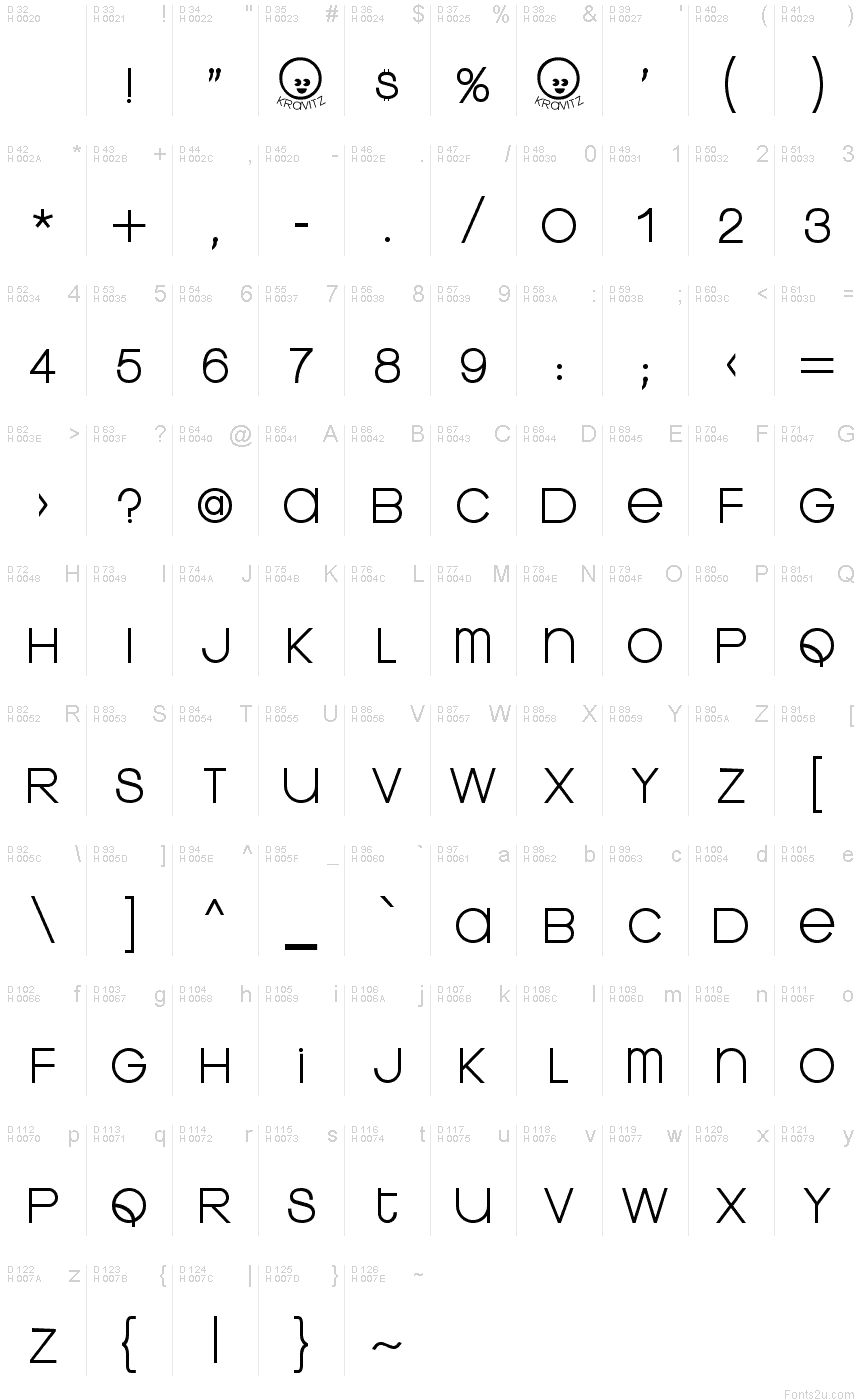
Kravitz Thermal od Fontalicious Fonts to bezpłatny, geometryczny font typu display, oparty na surowej, monolinearnej konstrukcji, szerokich, kolistych kształtach oraz długich przekątnych, dzięki którym litery zachowują ostrość i lekkość. Kontrast między niemal idealnymi krzywymi a ostrymi, kanciastymi cięciami nadaje krojowi wyrazisty, niemal znakowy rytm, odróżniający go od neutralnych krojów bezszeryfowych.
Ten font świetnie sprawdzi się na plakatach muzycznych, w logotypach modowych, tytułach wystaw, okładkach magazynów czy na opakowaniach technologicznych, wszędzie tam, gdzie krótkie napisy wymagają efektownej, graficznej sylwetki. Jego oszczędna konstrukcja pozwala również ciekawie wyeksponować branding, plansze tytułowe i duże cytaty, które zyskują dzięki zestawieniu kolistych form z ostrymi łączeniami.